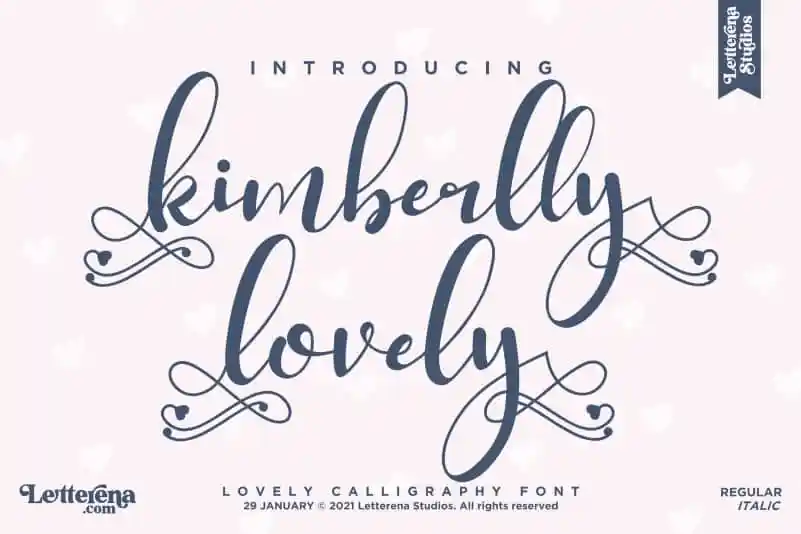
Kimberlly Lovely Calligraphy Font – Download Grátis
A Kimberlly Lovely Calligraphy Font é uma escolha perfeita para designers que buscam adicionar um toque romântico às suas criações digitais. Desenvolvida pela Letterenastudios, esta fonte calligrafia é ideal para diversos projetos, desde a criação de logomarcas e embalagens até ilustrações em livros ou materiais promocionais como camisetas e convites de festa. Proporcionando um visual elegante e delicado, Kimberlly Lovely atende perfeitamente tanto aos designers criativos quanto aos que buscam uma fonte única para seus projetos pessoais. Seja você um designer gráfico ou simplesmente um amante da arte digital, esta fonte oferece o toque final ideal para qualquer projeto onde a delicadeza e a expressão em letras script são desejadas. Não importa o tamanho do seu projeto – seja uma marca de sucesso, um design para sua cozinha de leitura ou até mesmo um anúncio especial para celebrar algo significativo – Kimberlly Lovely está aqui para torná-lo mais belo e atraente.